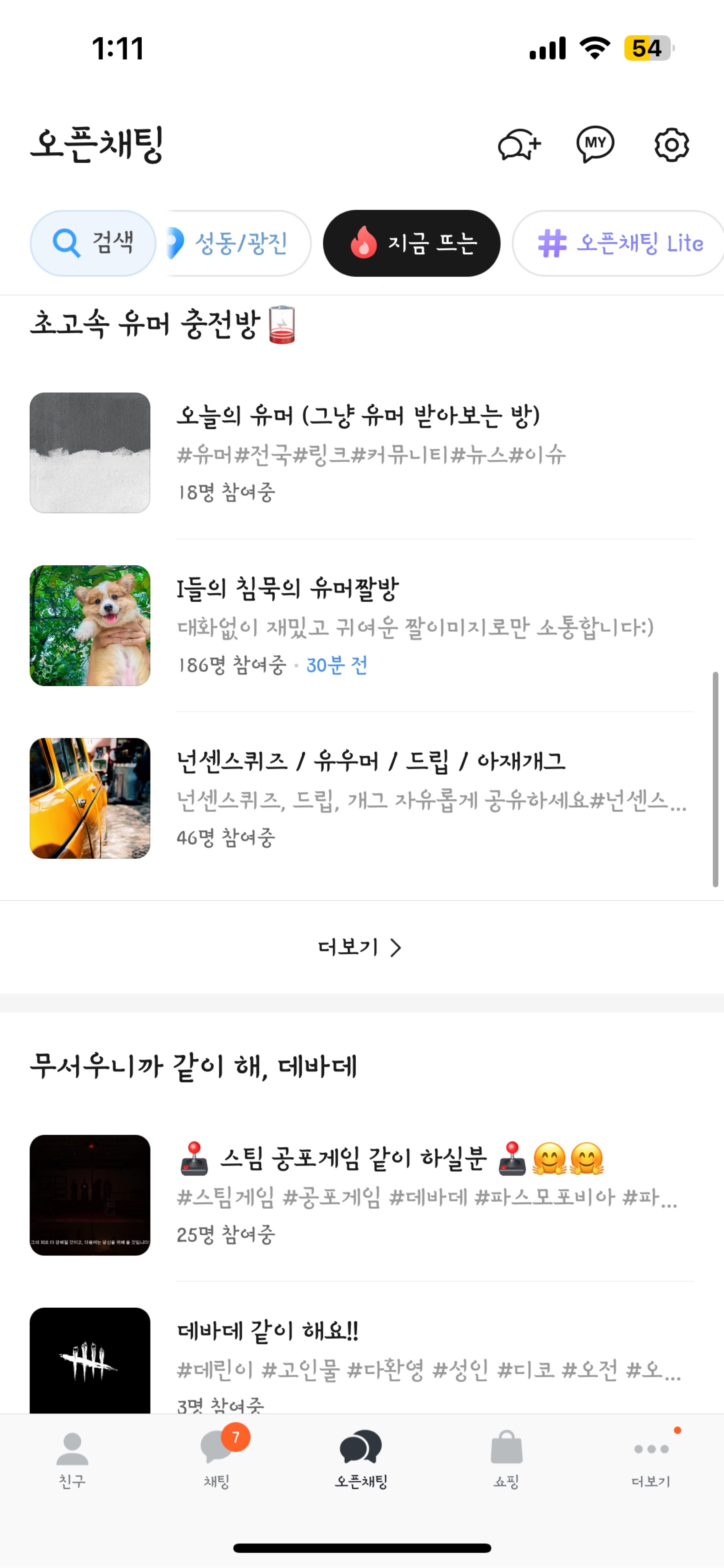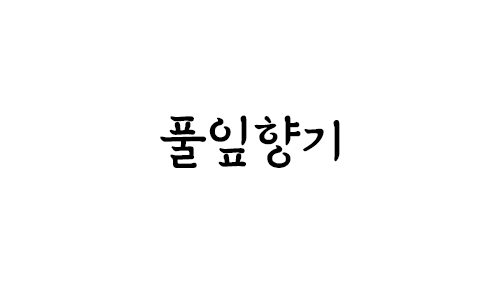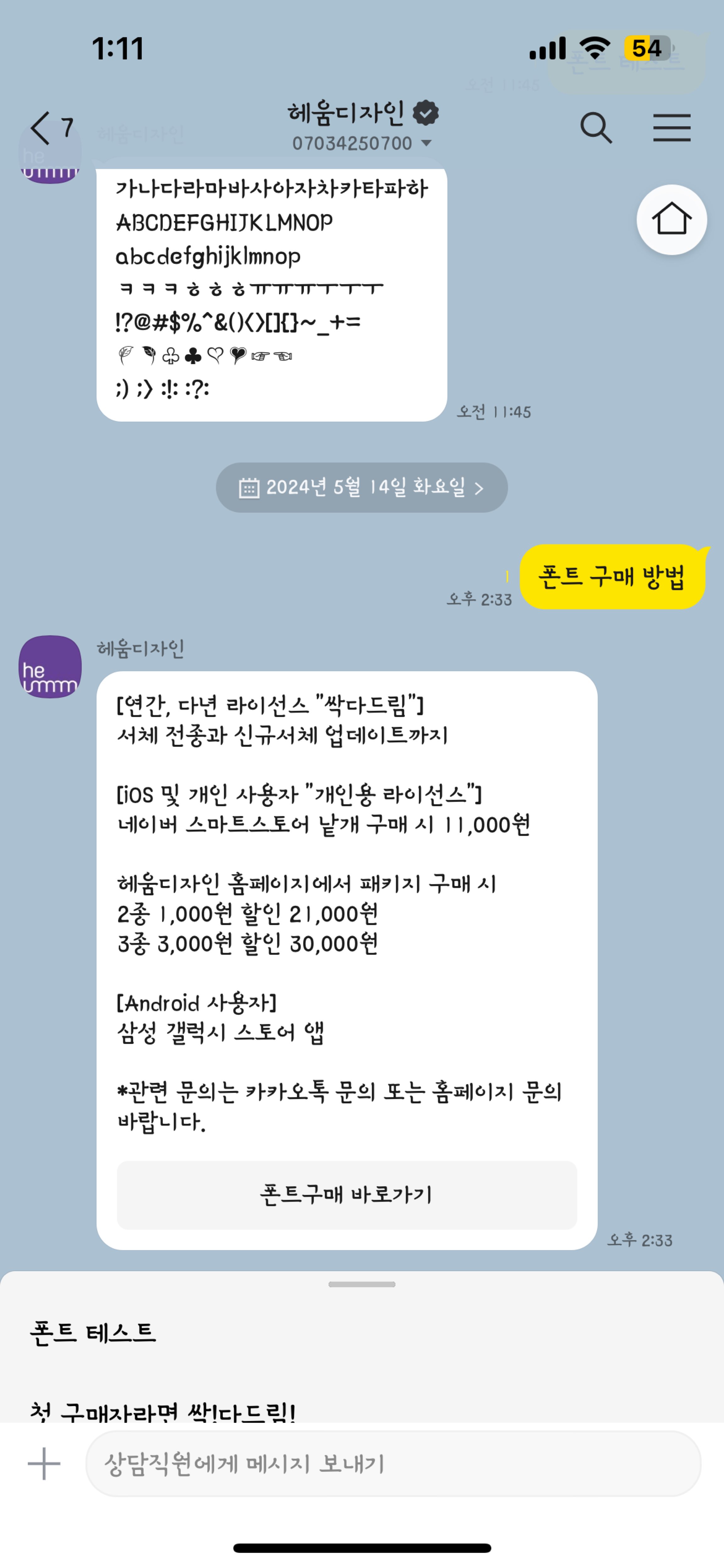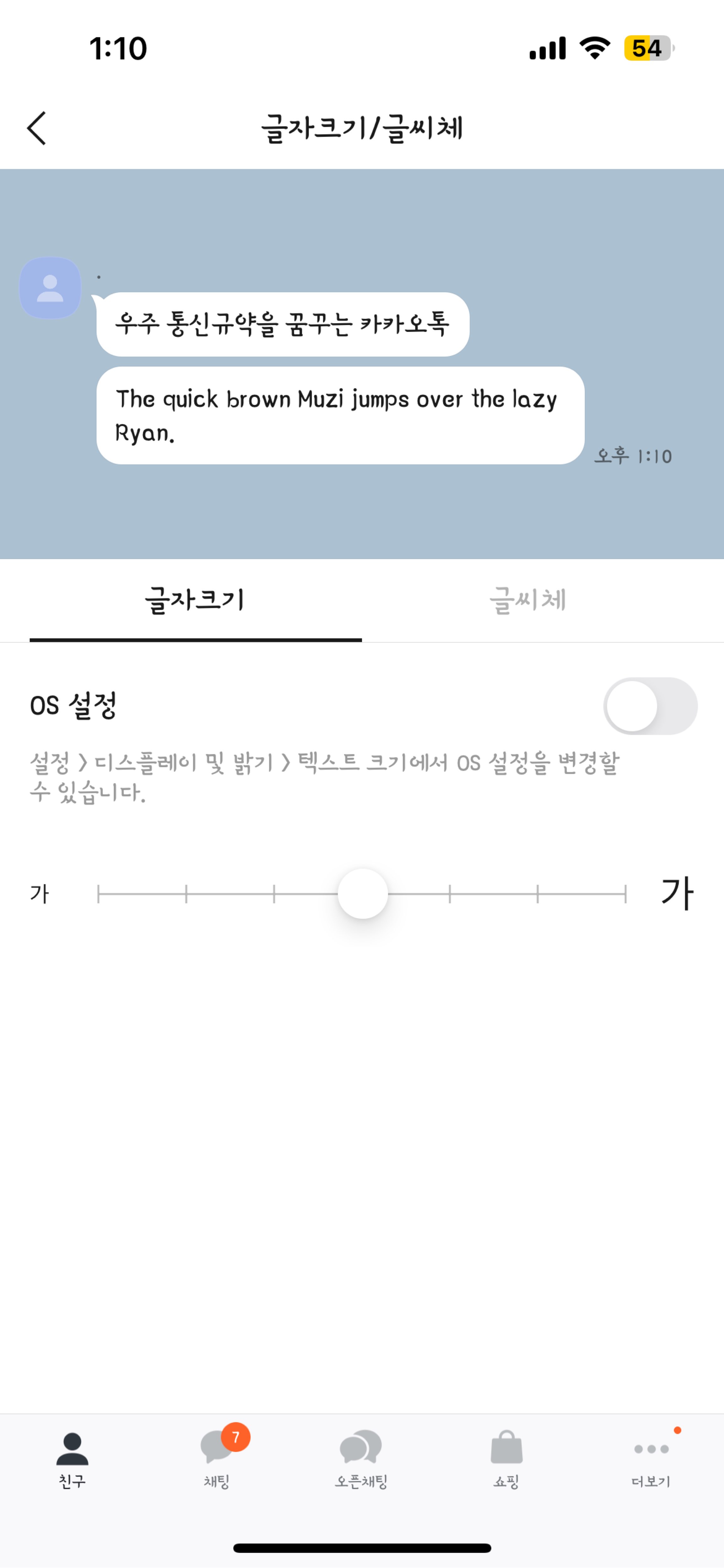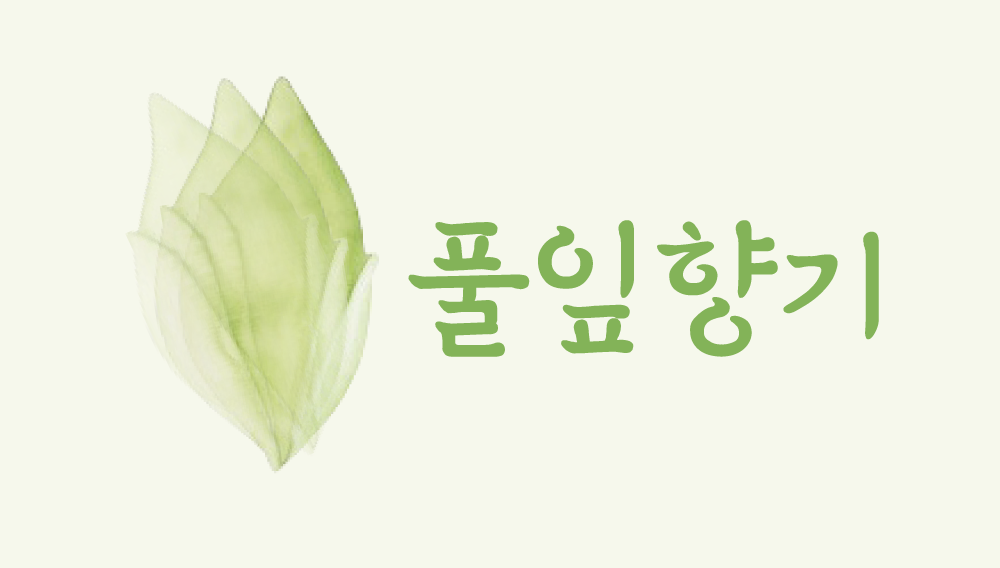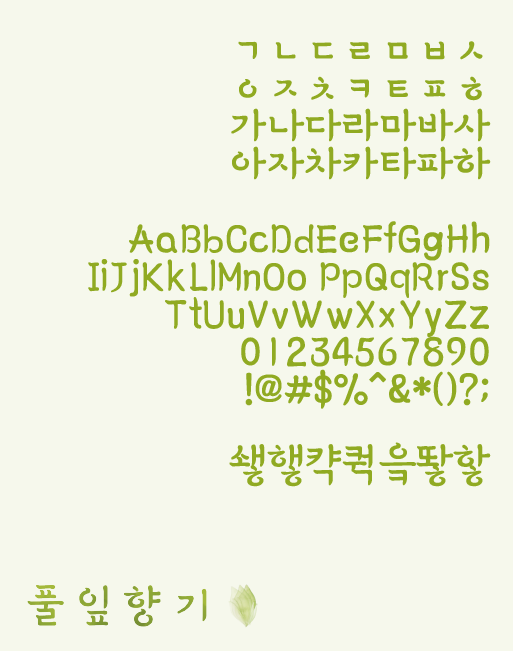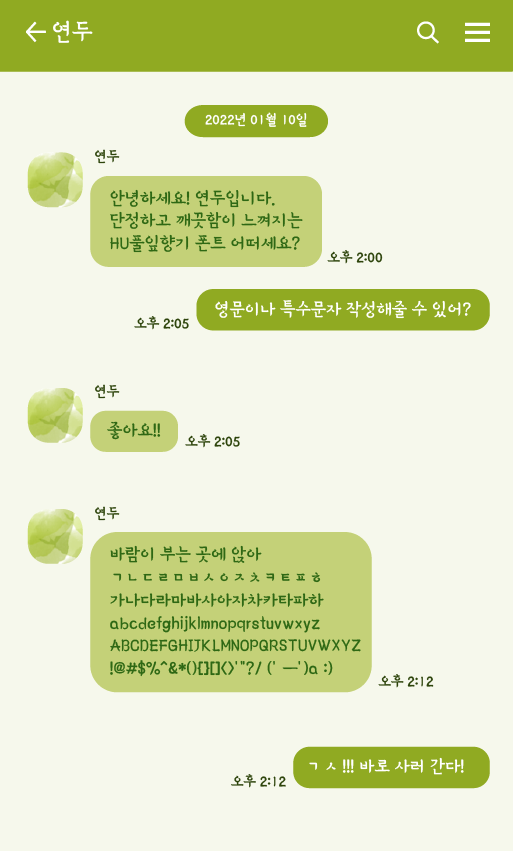
폰트      HU풀잎향기
굵기      2종
기간      2011
종류      #손글씨 #모바일
구성      KS한글 2,350자(130, 150)
KS한글 11, 172자(모바일)
풀잎에서 모티브를 얻어 제작, 강함과 부드러움이 함께 어우러진 서체입니다.
HU풀잎향기130
오랫동안 꿈을 그리는 사람은 마침내 그 꿈을 닮아간다.
HU풀잎향기150
오랫동안 꿈을 그리는 사람은 마침내 그 꿈을 닮아간다.